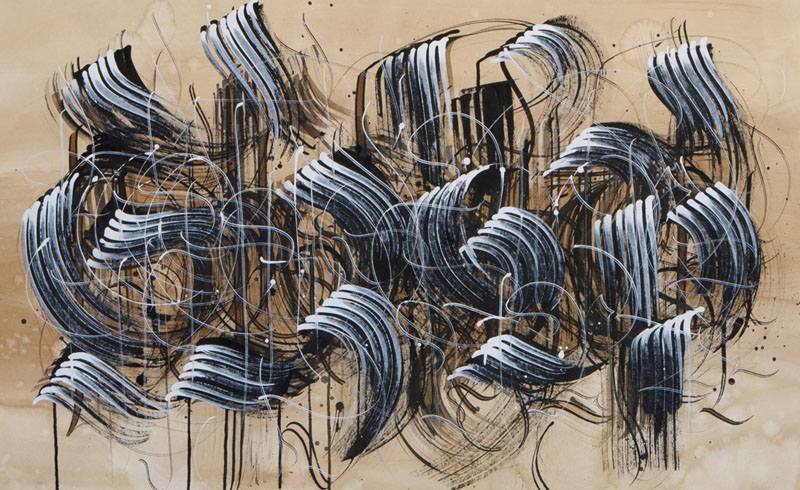
Blackletter Experiments /// Woserin
Blackletter
Experiments
In dieser Woche stehen die »Gebrochenen Schriften« (eher als Fraktur bekannt) im Mittelpunkt.
Der Workshop beginnt mit einer kurzen, theoretischen Einführung über die geschichtlichen Hintergründen und die unterschiedlichsten Einsatzbereiche dieser wunderschönen und wieder hochmodernen Schriften.
Durch abwechslungsreiche Übungen erlernst Du im ersten Teil des Workshops die Grundelemente der Schrift auf spielerische Art und Weise. Aus diesen Elementen entstehen erste Buchstaben, Worte ... sowie Sätze in der typischen Schriftanmutung.
Sicher wirst Du schnell entdecken, dass diese Übungen nicht nur ein Aneinanderreihen von Buchstaben sind, sondern auch riesigen Spaß machen ... und zu Ruhe und Gelassenheit führen.
Im zweiten Teil des Workshops wird – teilweise mit ungewöhnlichen Schreibwerkzeugen – frei mit Buchstaben und Materialien experimentiert. Die Lesbarkeit wird hier nicht mehr an erster Stelle stehen. Die Aufmerksamkeit ist auf Struktur und Form gerichtet – ohne dabei den typischen Charakter der Gebrochenen Schriften zu verlassen.
Der dritte Teil ist der künstlerischen Gestaltung gewidmet. Erlerntes aus dem ersten und zweiten Teil des Workshops wird zu einer spannenden Komposition zusammen gebracht.
Neben eurem eigenen schriftkünstlerischem »Abschlusswerk« nehmt ihr sicher viele professionelle Anregungen, eine »neue« Betrachtungsweise zur Gestaltung sowie historisches Hintergrundwissen mit nach Hause ... eine Basis für deine weitere Arbeit im Bereich »Kalligrafie«.